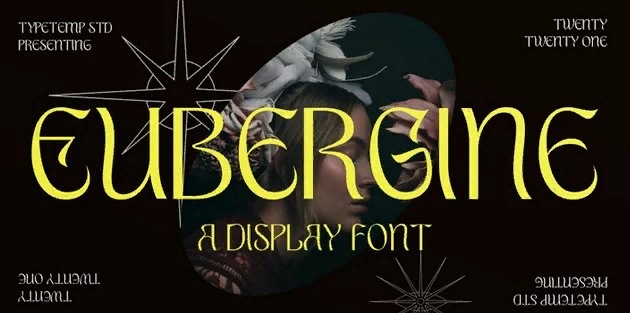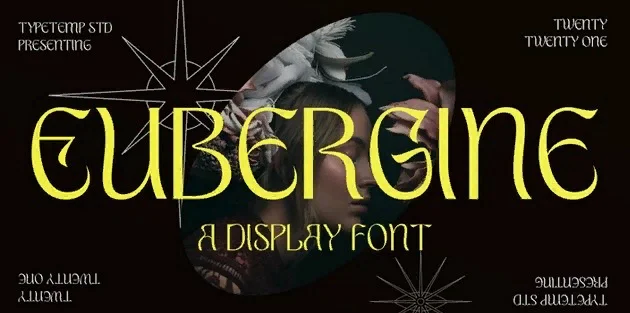
Название: Eubergine Font (2021)
EUBERGINE - Display дополнен некоторыми такими же альтернативами, сделанными с любовью. Используйте возможности OpenType для доступа к большому выбору альтернативных букв и лигатур, выберите понравившиеся буквы из большого разнообразия, чтобы получить дисплейный шрифт, который вам нравится. Отлично подходит для редакционных проектов, дизайна логотипов, брендинга одежды, упаковки товаров, заголовков журналов или просто как стильное наложение текста на любое фоновое изображение.